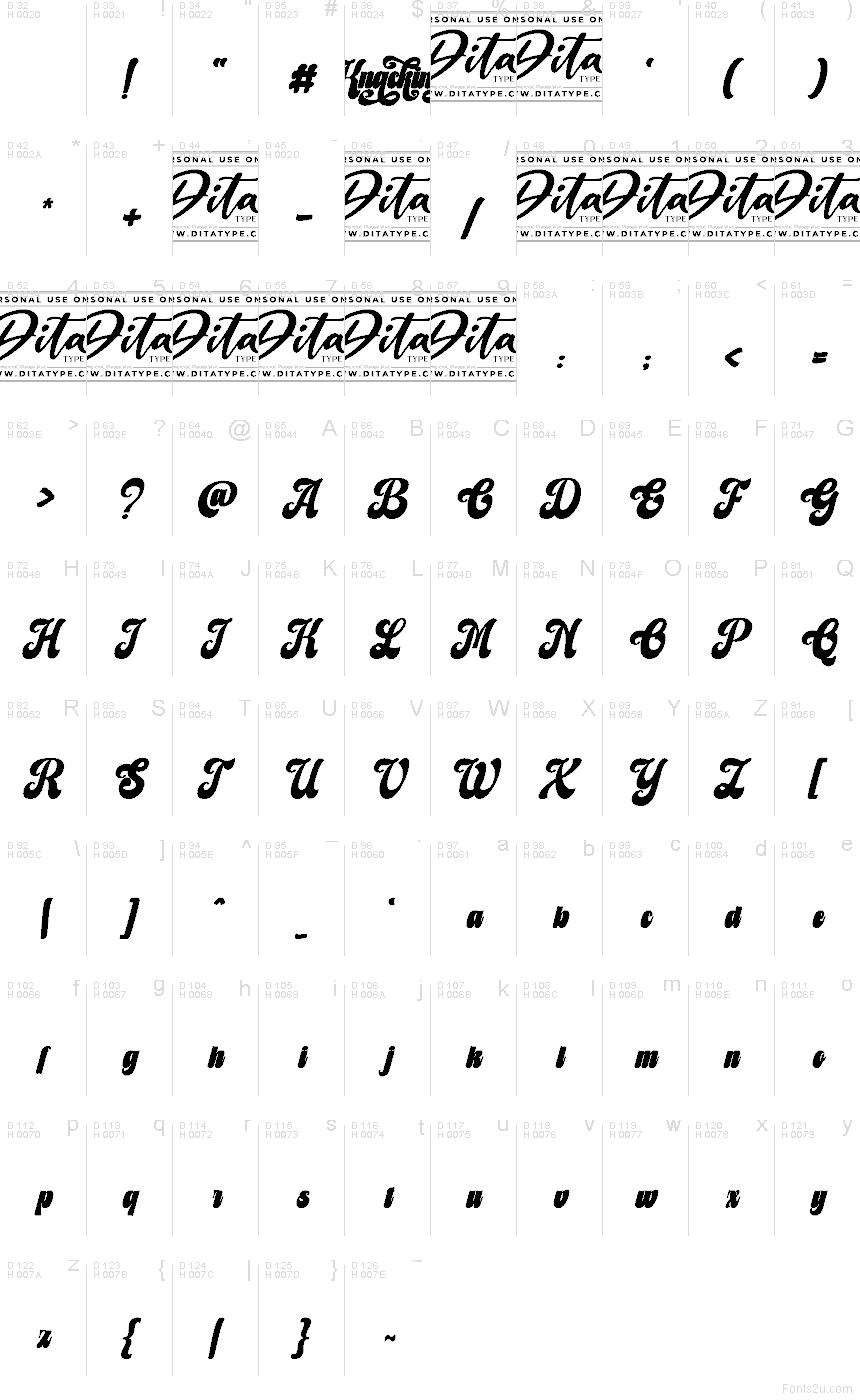
Knacking od Ditatype je bezplatné písmo typu brush s propojeným rukopisným stylem a zaoblenými, ručně kreslenými tahy. Písmena na sebe navazují hladkými křivkami a výrazným, malířským rytmem, což dodává nápisům živý, téměř signační charakter, aniž by působily příliš strnule.
Knacking je bezplatné písmo, které výborně vynikne v logách, grafikách pro sociální sítě, na obalech produktů, v nabídkách kaváren, při tvorbě citátů či krátkých plakátových textech, protože jeho štětcový styl vnáší do krátkých bloků textu jasný, ručně vyrobený akcent. Hodí se také pro design etiket a budování značky, kde díky ležérním, rukopisným tahům působí text osobně a přímo.